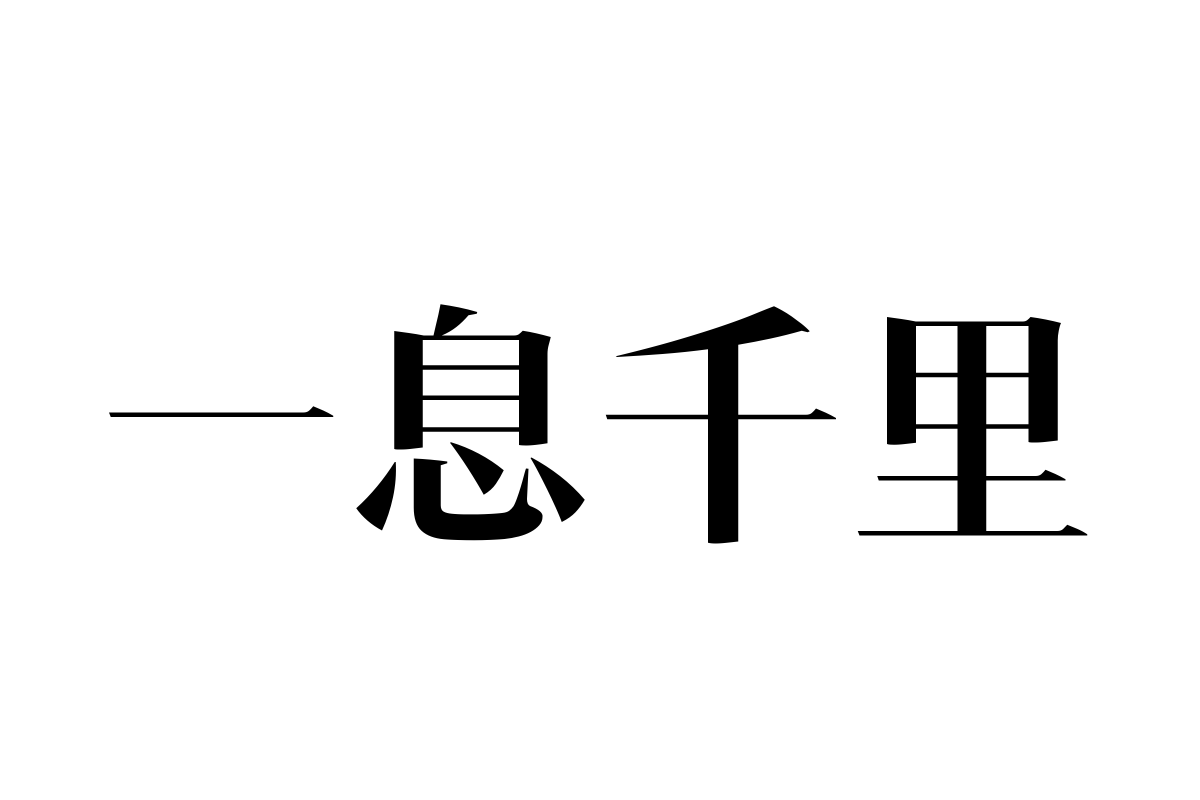
汉仪瑞意宋_75W 是一款具有现代感的宋体字体,适用于多种应用场景。这款字体的设计灵感来源于中国传统文化中的吉祥图案,如云纹、龙凤等元素,使得整个字型充满了浓厚的文化气息和艺术感。
汉仪瑞意宋_75W 的笔画粗细适中,既有楷书的规整,又有行书的流畅。它的字形结构严谨,线条流畅,给人一种优雅而庄重的感觉。同时,这款字体也具有较强的可读性,无论是在正式的商务场合还是在创意的文艺作品中,都能展现出其独特的魅力。
总的来说,汉仪瑞意宋_75W 是一款适合现代设计需求的宋体字体,无论是用于印刷出版还是网络设计,都能为作品增添一份独特的艺术韵味。